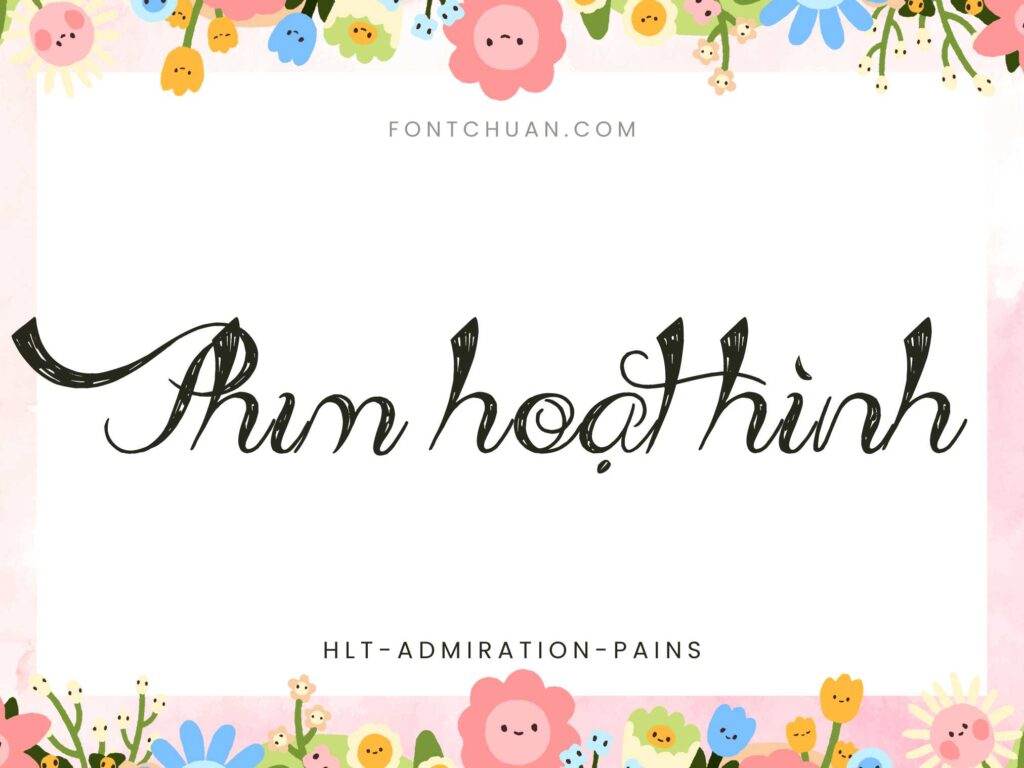
Font HLT Admiration Pains Việt Hóa
Admiration Pains là một kiểu chữ viết tay nghệ thuật, được thiết kế bởi Jonathan S. Harris và phát hành vào năm 2013. Font này mang phong cách thư pháp tinh tế, với các đường nét mềm mại và uyển chuyển, tạo nên sự độc đáo và thu hút cho các thiết kế. Với sự Việt hóa của HLT, Admiration Pains hỗ trợ đầy đủ các ký tự tiếng Việt, giúp người dùng dễ dàng áp dụng trong các dự án đa ngôn ngữ. Thành viên của Font Chuẩn đã sưu tầm và chia sẻ font chữ này nhằm đáp ứng nhu cầu của cộng đồng thiết kế.
Về đặc điểm thiết kế, Admiration Pains bao gồm các ký tự hoa mỹ với độ tương phản cao, mang lại cảm giác thanh lịch và nghệ thuật. Font này đặc biệt phù hợp cho các dự án thiết kế như thiệp mời, bìa sách, poster, logo và các ấn phẩm quảng cáo, nơi cần sự nhấn mạnh và ấn tượng mạnh mẽ. Ngoài ra, Admiration Pains cũng thích hợp cho các sự kiện như lễ hội, sinh nhật, Valentine và Trung thu, mang lại không khí ấm áp và gần gũi. Trong lĩnh vực ngành nghề, font này được ứng dụng rộng rãi trong quảng cáo, thiết kế thiệp cưới, giáo dục và công nghệ, góp phần tạo nên sự độc đáo và thu hút cho các sản phẩm và thương hiệu.